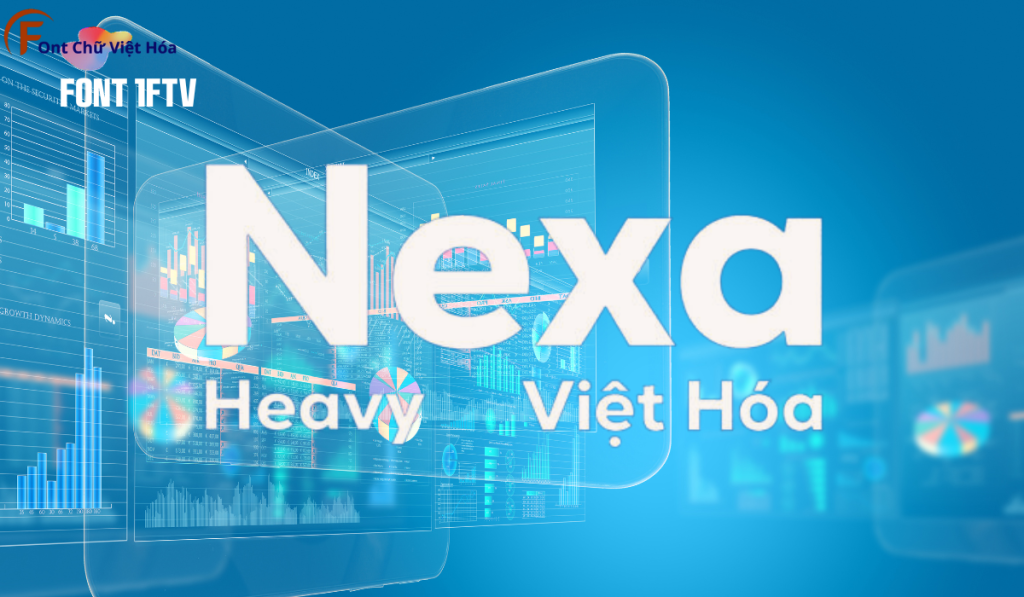
Font 1FTV Nexa Heavy
Tác giả: 1FTV Nexa Heavy
Bộ Font: 1FTV
Kiểu chữ: Sans-serif
Độ dày: Heavy
Font 1FTV Nexa Heavy là một font chữ độc đáo, thuộc bộ 1FTV, nổi bật với phong cách sans-serif hiện đại và các đường nét mạnh mẽ, cá tính. Thiết kế của 1FTV Nexa Heavy tập trung vào sự rõ ràng và dễ đọc, đặc biệt phù hợp cho các thiết kế đòi hỏi tính thẩm mỹ cao như poster, logo, và tiêu đề. Với tỷ lệ chữ cân đối và các đường nét đậm, font này tạo ra ấn tượng thị giác mạnh mẽ và giúp tối ưu hóa không gian trong thiết kế. Font này cũng đã được Việt hóa, mang đến sự linh hoạt và tiện dụng cho các dự án thiết kế bằng tiếng Việt.